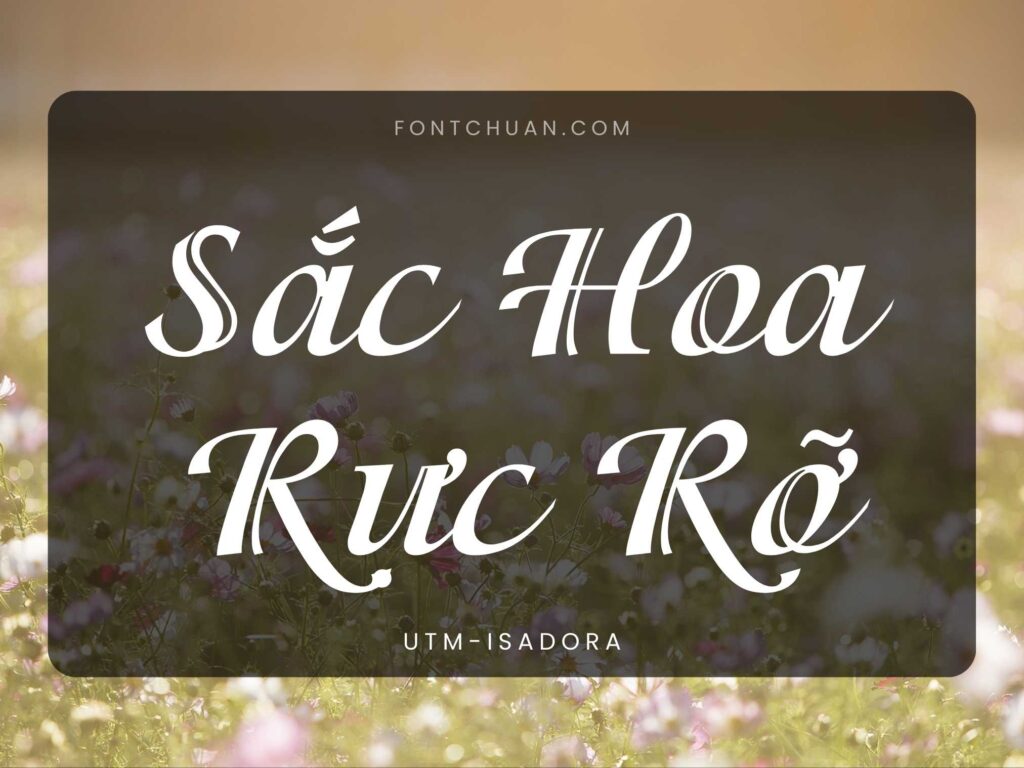
Font UTM Isadora Việt Hóa
UTM Isadora là một font chữ thanh lịch, mang phong cách cổ điển kết hợp với sự hiện đại, tạo nên vẻ đẹp tinh tế và mềm mại. Font này được thiết kế để mang đến sự sang trọng trong các ấn phẩm thiết kế đồ họa. Font đã được Việt hóa bởi Thiên Minh, hỗ trợ đầy đủ tiếng Việt cùng hơn 200 ngôn ngữ khác, giúp mở rộng khả năng sử dụng. Thành viên của Font Chuẩn đã sưu tầm và giới thiệu font này nhằm đáp ứng nhu cầu bạn đọc, cung cấp nguồn tham khảo chất lượng và ứng dụng thực tế vào các dự án thiết kế
Về đặc điểm thiết kế, UTM Isadora có các đường nét uyển chuyển, độ tương phản nhẹ và kiểu chữ tinh tế. Font này phù hợp với nhiều ứng dụng như thiết kế thương hiệu, thiệp mời, biển hiệu, tiêu đề trang web và các ấn phẩm sáng tạo. Các ngành nghề như quảng cáo, ẩm thực, thiệp cưới và giáo dục có thể tận dụng font này để tạo điểm nhấn, mang đến sự thanh lịch trong các sản phẩm thiết kế. Đặc biệt, với các ấn phẩm giáo dục như sách, bài giảng hay tài liệu học tập, UTM Isadora có thể được sử dụng như một Font chữ giáo dục lý tưởng, vừa dễ đọc, vừa tinh tế, giúp nâng cao trải nghiệm học tập.
Bên cạnh các ứng dụng chuyên nghiệp, UTM Isadora còn là một Font valentine lý tưởng để thiết kế các sản phẩm lãng mạn và ngọt ngào, như thiệp Valentine, banner kỷ niệm hay poster dịp lễ tình nhân. Với các đường nét uyển chuyển, tinh tế, font này giúp tạo cảm giác mềm mại, sang trọng và ấm áp, mang đến trải nghiệm trực quan gần gũi nhưng vẫn đầy tinh tế cho các dự án thiết kế.